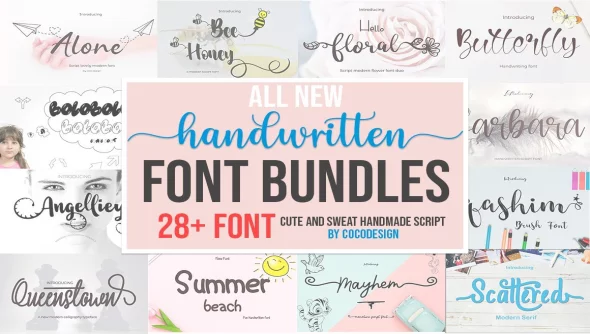
تخفيضات كبيرة حزمة الخطوط المكتوبة بخط اليد
هذه الحزمة مثالية لبطاقات المعايدة والعلامات التجارية وبطاقات العمل والاقتباسات والملصقات والمدونات والشعارات وحفلات الزفاف واللافتات والتعبئة وإعلانات الميلاد وتراكبات الصور وفنون الجدران والاقتباسات والمواد المطبوعة والحقائب والقمصان والمزيد . . .
Big sale handwritten font bundle
Aladin
Alone
Angelliey
Arjudah
Back Later
Barbara
Bargot
Bee Honey
Bhatique
Black Hawn
Butterfly
Full Out
Full Out Bonus
Graffiti Stroke
Habbit
Hello Floral
Holliwing
Mariana
Mayhem
Mayhem Bonus
Milk Sheep
Minnie
Minnie Bonus
Qashim
Queenstown
Scattered
Scooter
Senyawa
Singway
Stay Work
Stay Work Bonus
Summer Beach